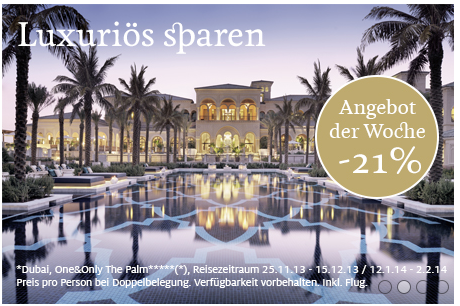
Kuoni-Font gesucht
Welchen Font verwendet der Schweizer Luxus-Reiseveranstalter Kuoni als Copyschrift?
Besonders auffällig sind die schönen Ligaturen...